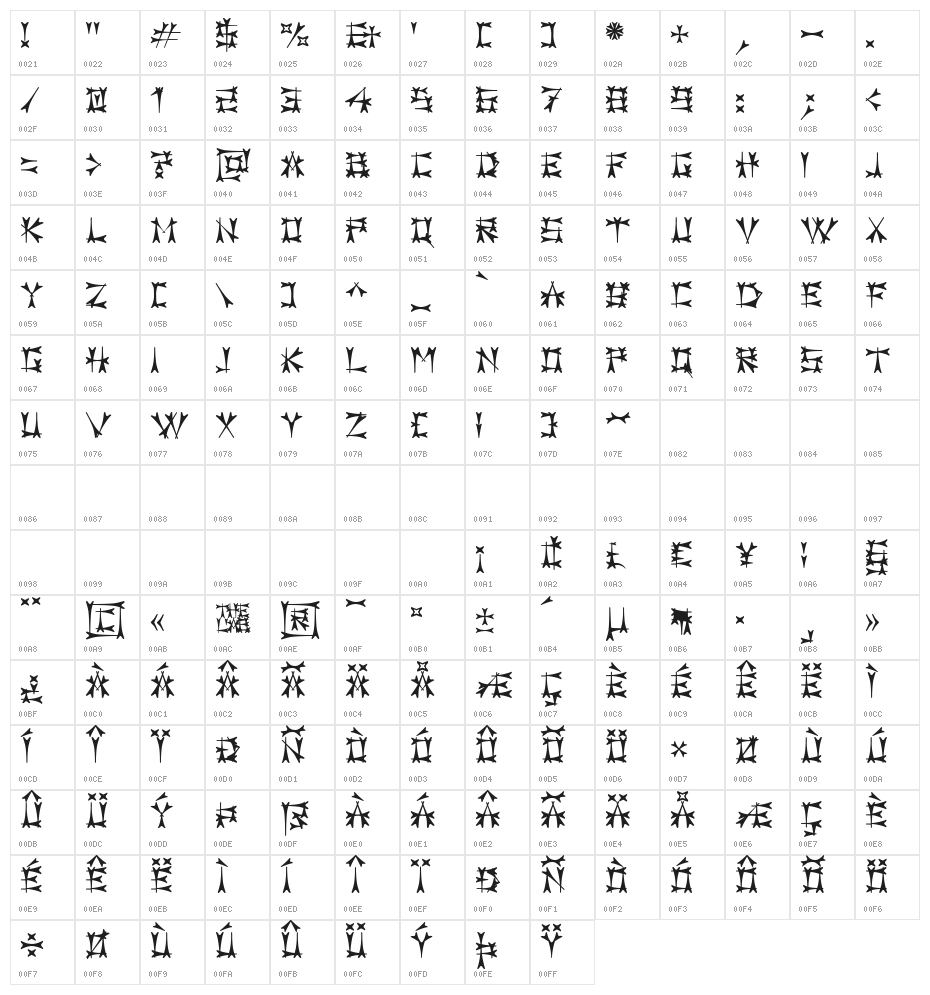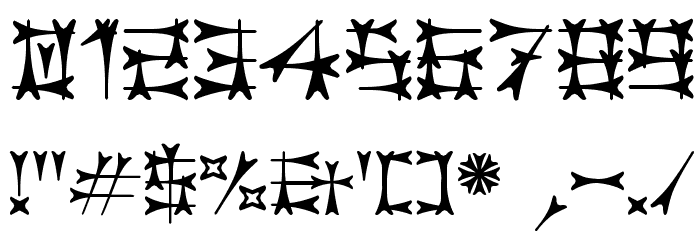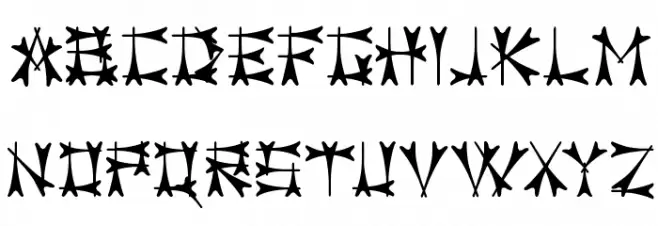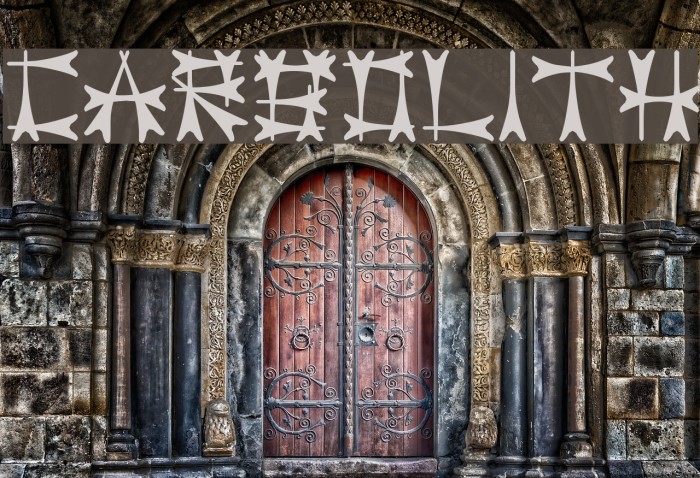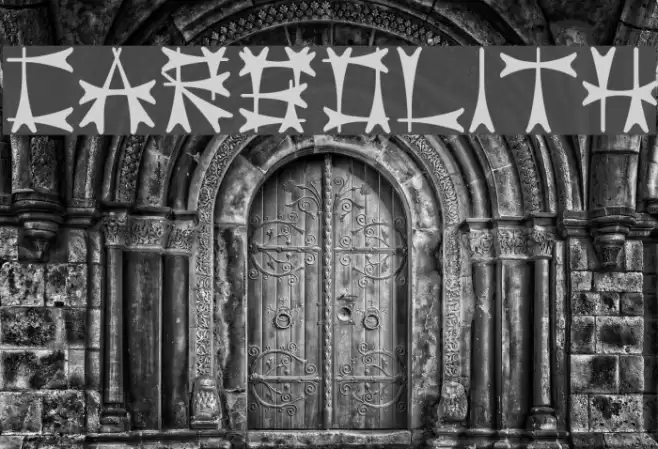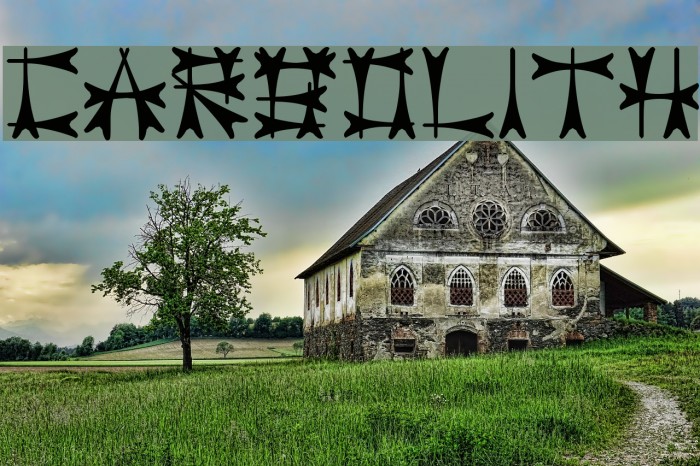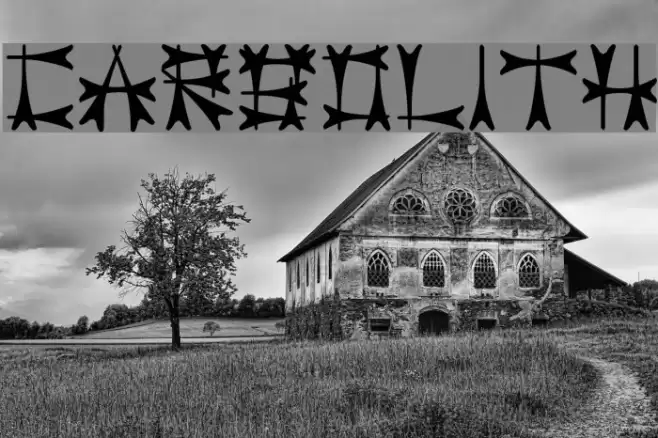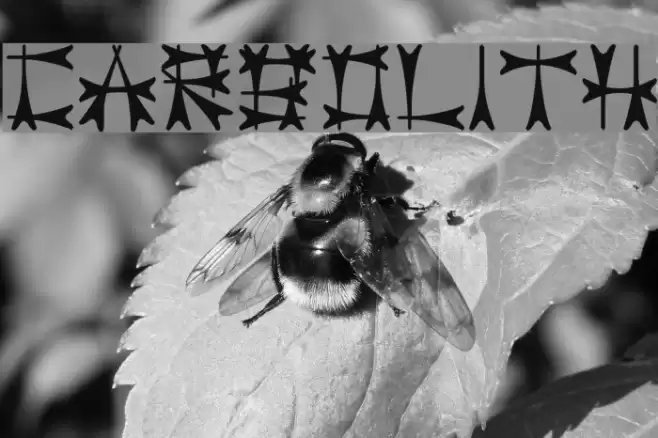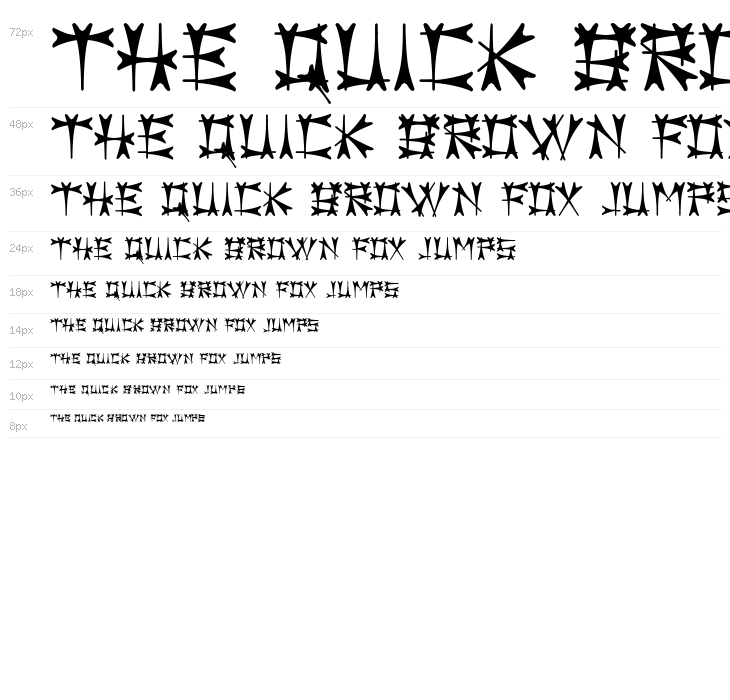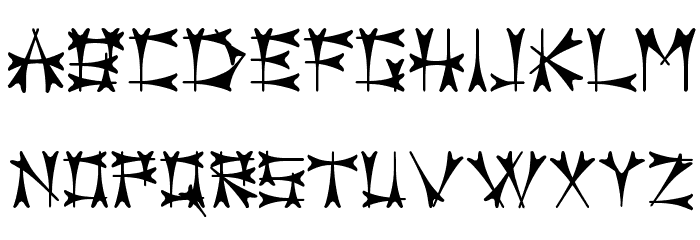
Carbolith Font
| Kategorien | Decorative |
| Gesamtstil | Modern, Decorative |
| Anwendungsfall | Logos, Posters, Album Covers |
| Vorgeschlagene Projekte | Ideal for album covers, posters, branding for edgy or alternative products, and any design needing a bold statement. |